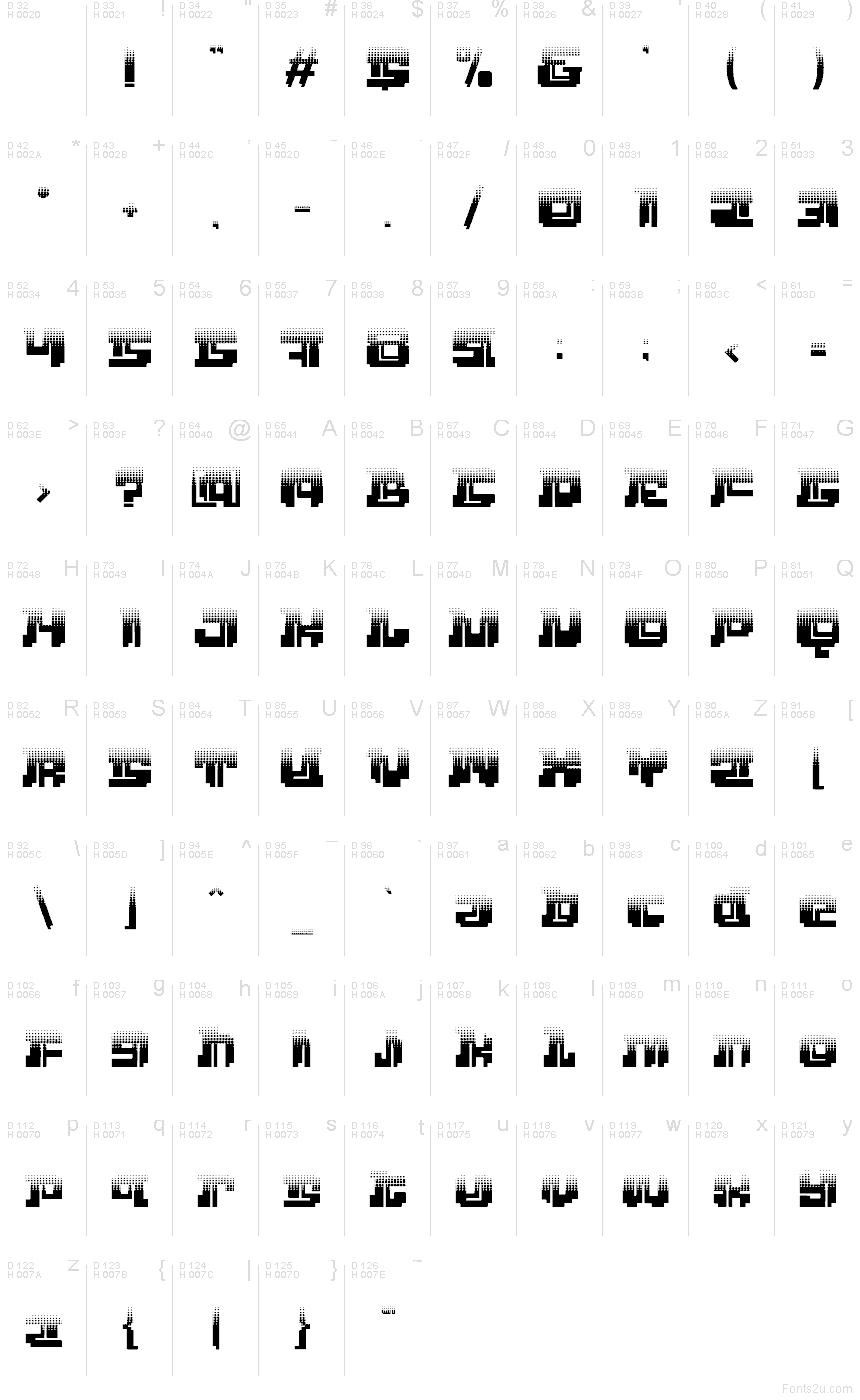
Techno Wave Three od Putracetol Studio je bezplatné futuristické písmo typu display, definované konstrukcí přecházející z polotónů do plných ploch, díky čemuž každé písmeno vypadá, jako by vypadávalo z digitální mřížky. Opakující se řady čtvercových bodů vytvářejí odstupňovanou, signálu podobnou texturu, zatímco tmavší spodní části udržují design pevně při zemi, takže nepůsobí jen vzdušně nebo dekorativně.
Tento grafický přechod dodává krátkým titulkům přirozený prostor v herních nabídkách, sci-fi plakátech, pozvánkách na akce, náhledech YouTube videí a technologickém brandingu. Může také dodat ostrost obalům alb nebo grafice pro streamy, kde pixelovaný horní okraj připomíná obrazovky, ekvalizéry a elektronická rozhraní spíše než běžný styl zobrazení.